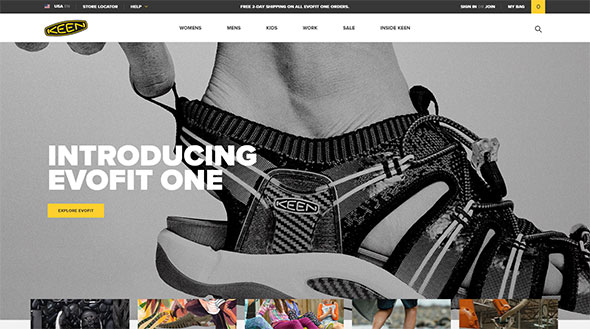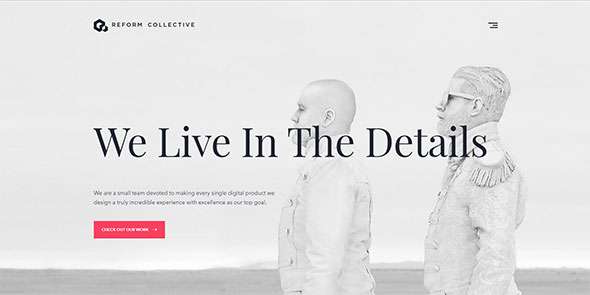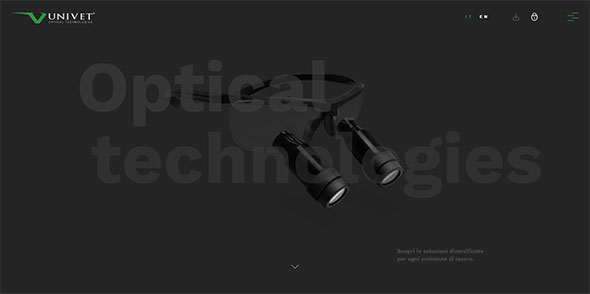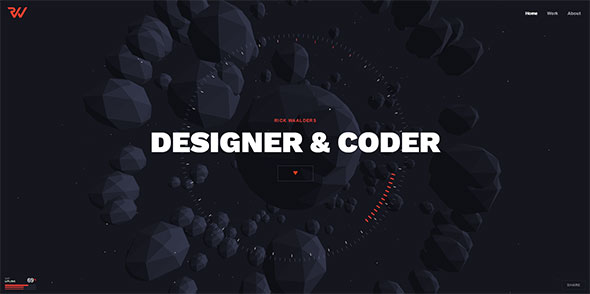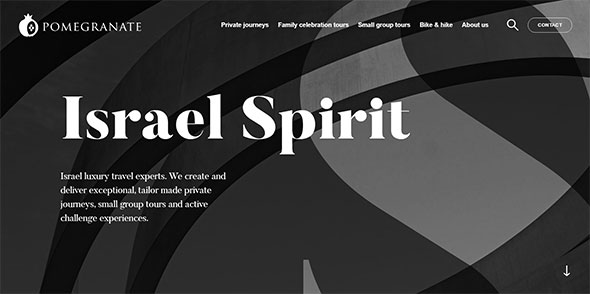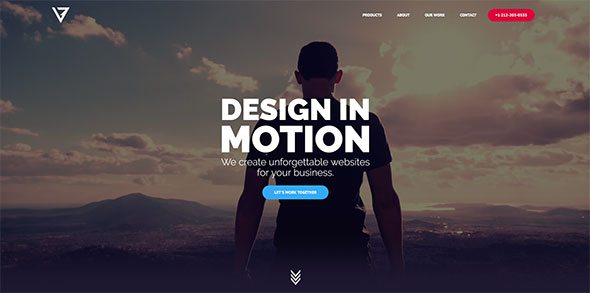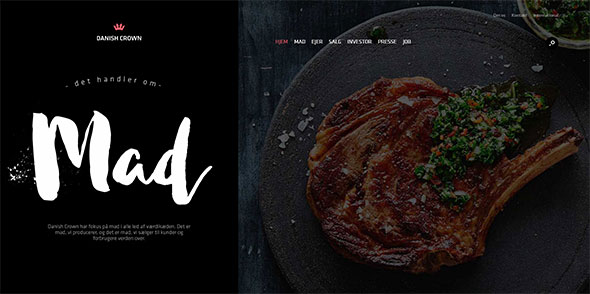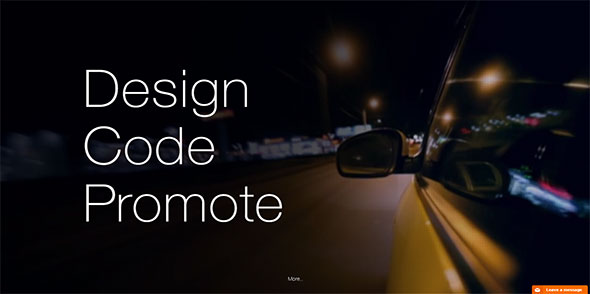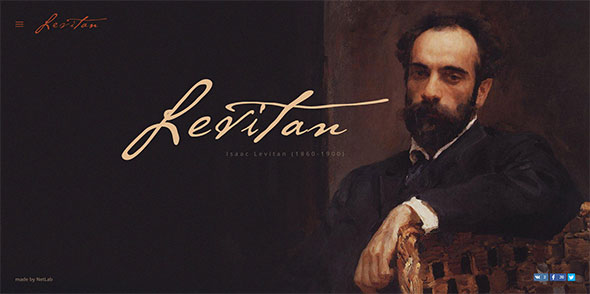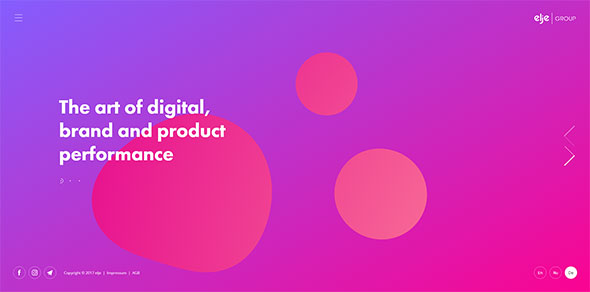
Крупный шрифт в веб-дизайне
Еще один не проходящий тренд в веб-дизайне – большая типографика. Крупные заголовки и надписи выглядят стильно, хорошо читаются и привлекают внимание посетителей. Сегодня мы собрали примеры этого модного решения в веб-дизайне, и делимся с вами нашими находками. Смотрите и вдохновляйтесь!